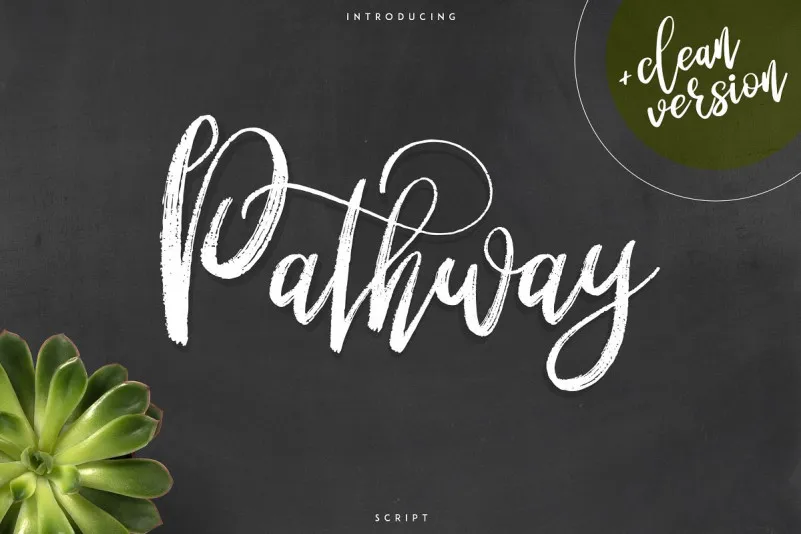
Pathway Script Font – Download Grátis
Esta é uma nova face de tipo feita à mão com esfincios, apresentando um conjunto de caracteres elegante e vintage. É chamada Pathway Brush Font, criada pelo designer VPcreativeshop, que agora está disponível para download grátis. Este estilo script foi elaborado manualmente, oferecendo duas estilos distintos, suportando várias línguas, tornando-o extremamente versátil para diferentes aplicativos. Perfeito tanto para projetos de branding e design de móveis à casa como para embalagens de produtos ou cabeçalhos de revistas, Pathway Script Font também se destaca como uma excelente opção para textos decorativos sobre qualquer imagem de fundo. Não perca esta oportunidade única para adicionar um toque único ao seu trabalho gráfico com este script elegante e vintage.